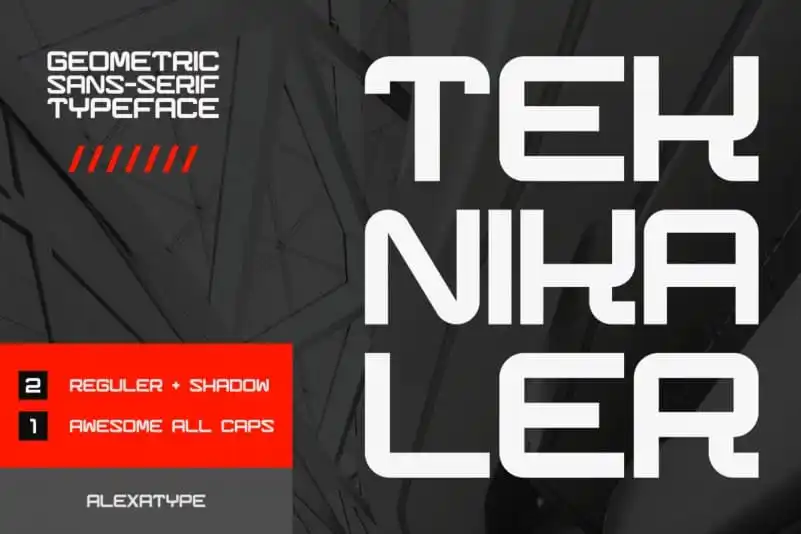
Teknikaler Display Font é uma tipografia de display que transpira otimismo, alegria e encanto. Criada pelo designer Alexatype, esta fonte sans-serif geométrica tem formas retangulares com ângulos arredondados perfeitamente adaptadas para artigos tecnológicos modernos, postais, sites e materiais promocionais de qualquer tamanho. Suas letras em maiúsculas completas vêm em duas estilos: regular e com sombra. É perfeita tanto para logotipos como cartões de visita, layouts de revistas, convites, cabeçalhos ou até mesmo artesanato a grande escala. Esta fonte é uma ótima escolha para levar seu design à próxima dimensão.